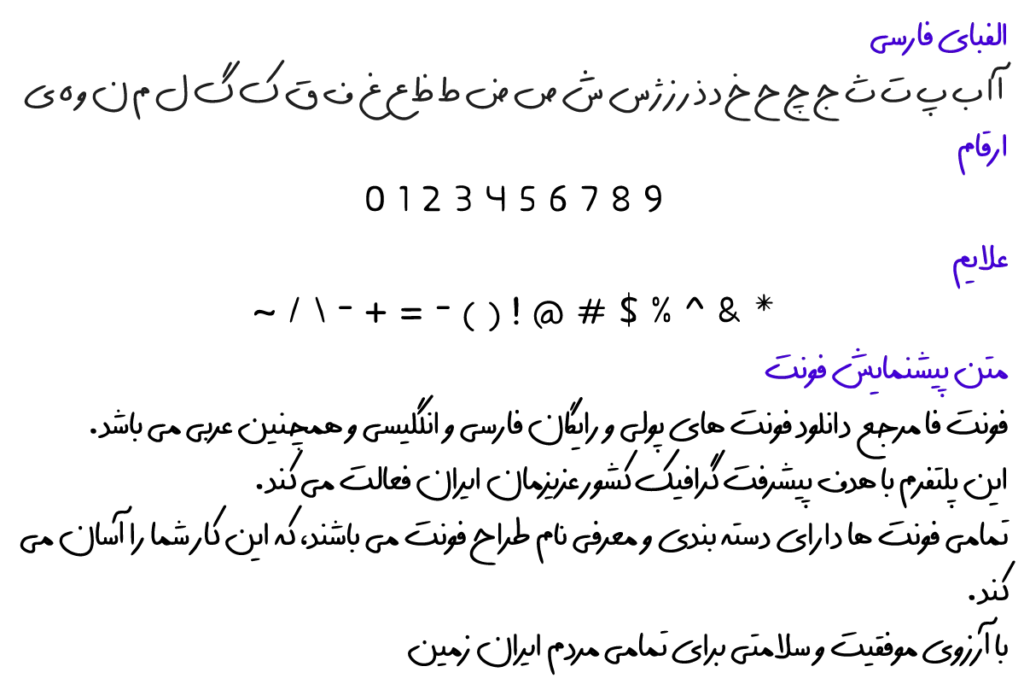
فونت فارسی پاییز 2 – Paeez Profesional
سال ساخت فونت: 1401
طراح فونت: مهدی برقگیر نوع فونت: فونت دست نویس
پیشنمایش فونت پاییز 2
توضیحات و معرفی فونت پاییز 2
فونت فارسی پاییز 2 ( Paeez Profesional ) از مجموعه فونت های برتر و سری Digi می باشد، همچنان نوع فونت دست نویس می باشد.
فونت شگفت انگیز و زیبای فوق توسط مهدی برقگیر در سال 1401 طراحی و ساخته شده است.
پاییز دو نسخه بهبود یافته فونت پاییز است، اما با کمی تغییر…
شعر زیبای وطنم نوشته شده با این تایپ فیس که میتوانید در عکس زیر تماشا کنید.